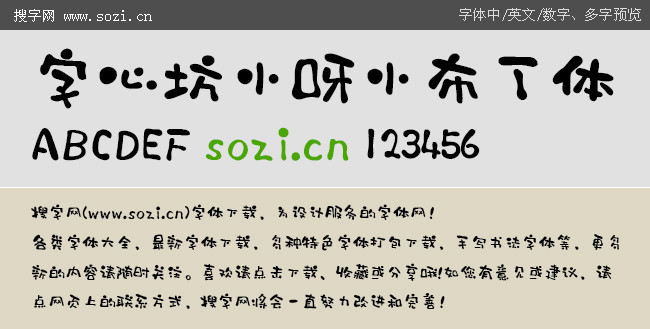
字心坊小呀小布丁
搜字網(wǎng)給大家提供一款字心坊小呀小布丁中文字體下載,字心坊小呀小布丁體是由字心坊推出的一款中文字體,該字體時(shí)尚大方,造型采用了可愛的布丁特色,筆畫圓溜溜的仿佛要跳動(dòng)起來(lái),字體的點(diǎn)看起來(lái)比較圓潤(rùn),而且結(jié)構(gòu)相當(dāng)?shù)亓鲿吵霰,適用于包裝印刷、海報(bào)設(shè)計(jì)等藝術(shù)設(shè)計(jì)應(yīng)用。(本字體為個(gè)人非商用版,如需要商用請(qǐng)聯(lián)系作者購(gòu)買版權(quán))